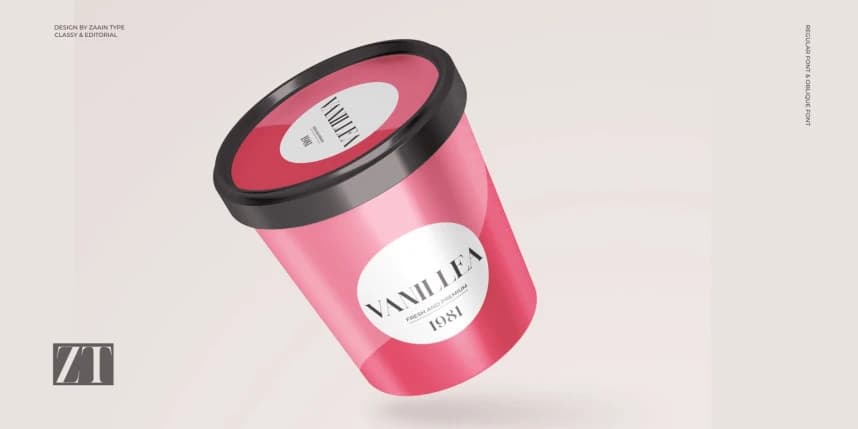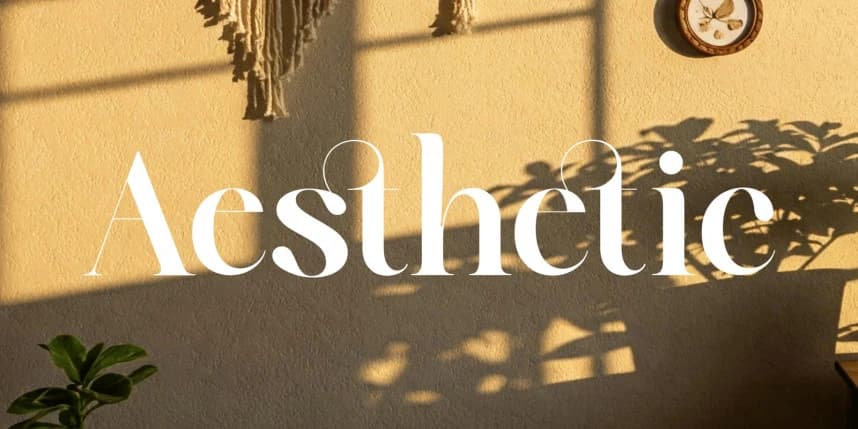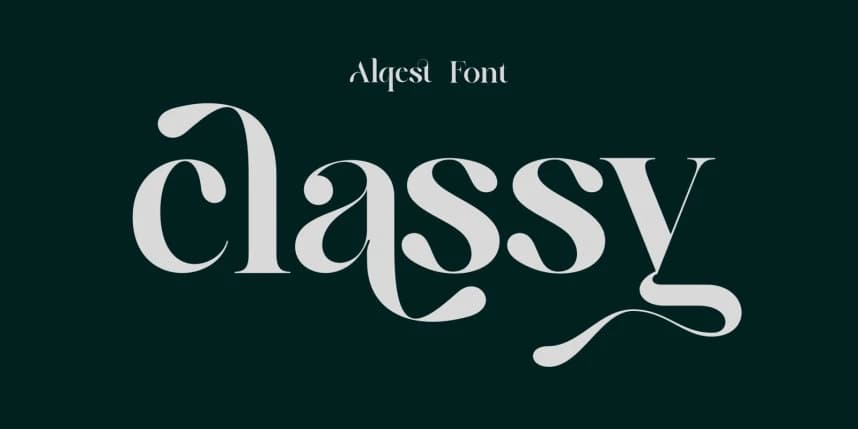
Alqest Yazı Tipi
Alqest Font, klasik zarafeti ince bir modern dokunuşla birleştiren bir serif yazı tipidir. Karakterleri dengeli oranlara sahip, akıcı kalın-ince kontrastı ve zarif serif detaylarıyla özenle tasarlanmıştır—aşırıya kaçmadan sofistike bir görünüm yaratır.
Alqest Font, klasik zarafeti ince bir modern dokunuşla birleştiren bir serif yazı tipidir. Karakterleri dengeli oranlarla, pürüzsüz kalın-ince kontrastla ve zarif serif ayrıntılarıyla özenle tasarlanmıştır—gereğinden fazla hissettirmeden sofistike bir görünüm yaratır.